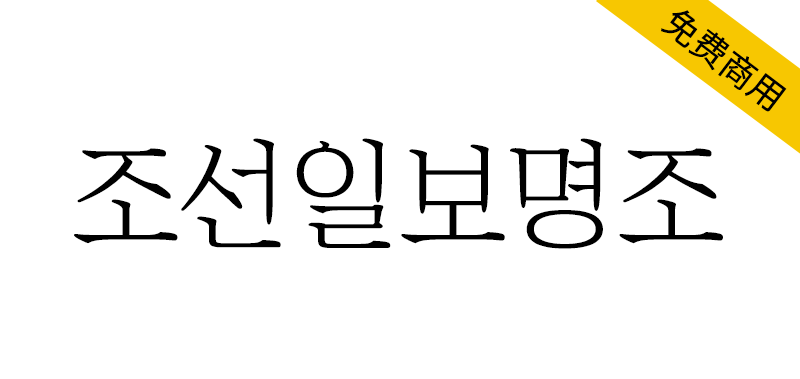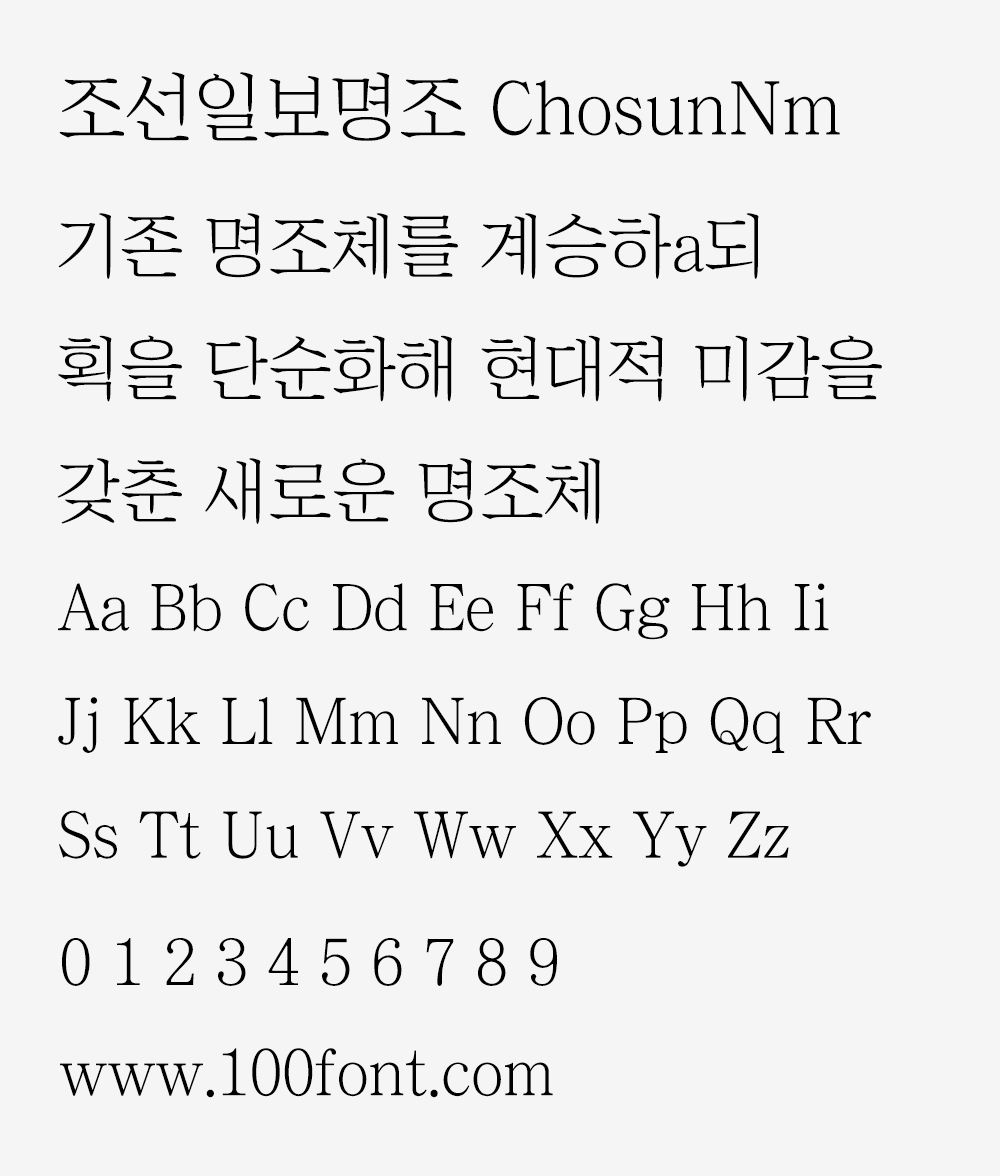
朝鲜媒体集团公开和普及报纸版面上使用的专用字体“朝鲜日报明朝体”,供任何人使用。《朝鲜日报明朝体》是1999年朝鲜日报字体开发研究所与“山石交流”制作的字体,之后总公司以一字一字的精神进行完善,提高了完成度。小尺寸使用也方便阅读,造型美观,深受读者喜爱,是受到专家好评的优秀铅字。准备好供普通PC和Mac用户使用。
조선미디어그룹은 신문 지면에 사용하는 전용 서체(書體)인 ‘조선일보 명조체’를 누구나 사용할 수 있도록 공개·보급합니다.
‘조선일보 명조체’는 1999년 조선일보 서체개발연구소가 ‘산돌커뮤니케이션’과 만든 서체로, 이후 본사가 한 글자 한 글자 인(匠人)정신으로 보완해 완성도를 높였습니다. 작은 크기로 사용해도 읽기 편하고, 조형미가 뛰어나 독자의 사랑과 함께 전문가들로부터 호평 받아온 우수한 활자입니다. 일반PC와 Mac 사용자 모두가 쓸 수 있도록 준비했습니다.